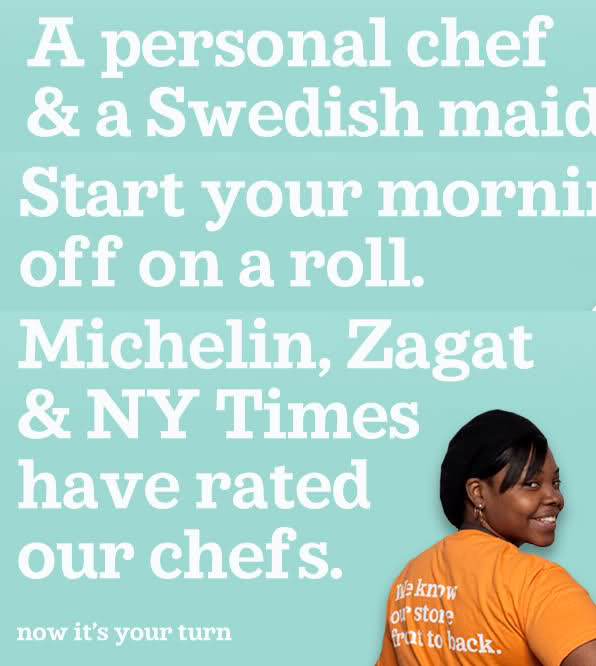
Slab Serif gesucht
wer kennt diese wunderschöne Slab-Serif? Sie sieht sehr "american" aus. Dachte erst es sei die Clarendon, aber die ist es nicht. Dann dachte ich, es wäre die Sentinel, aber das A ist ganz anders (diese hier hat so einen markanten Querbalken oben).
Hat jemand eine Ahnung wie diese Schrift heißt?
Oh, die Sentinel ist aber wirklich eine Schöne... -sabber- :D